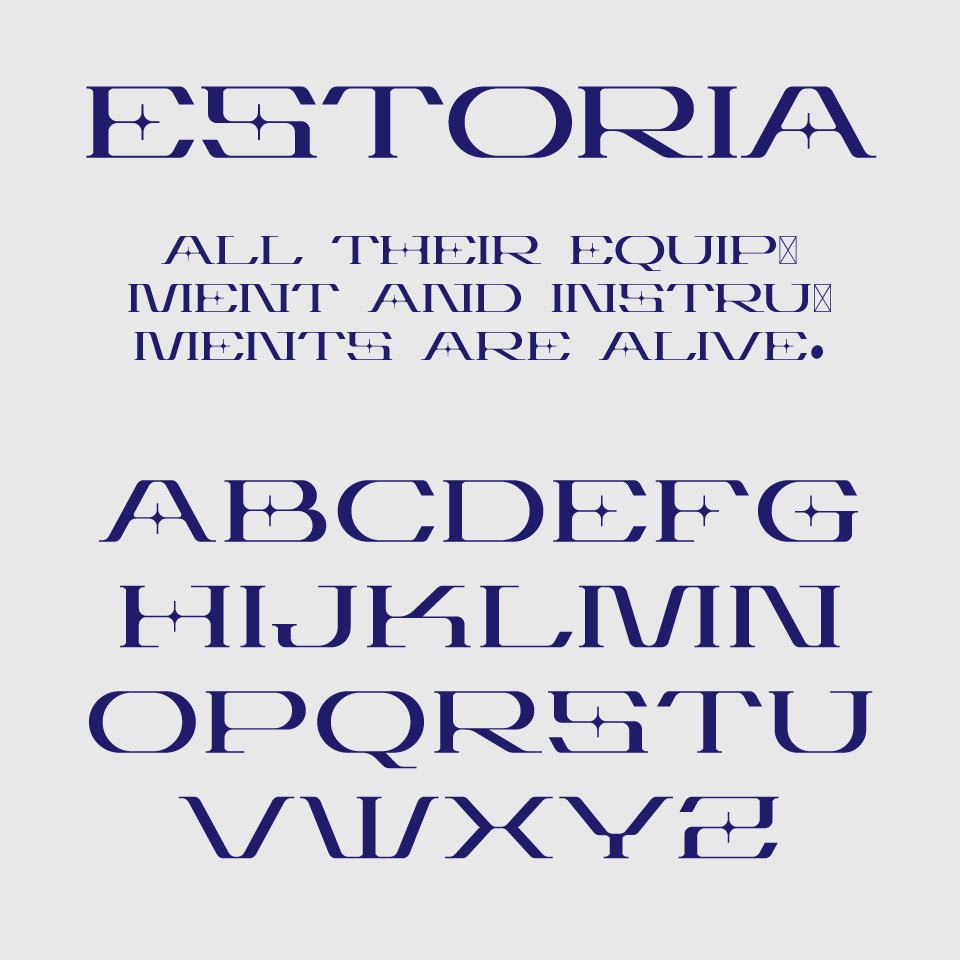
Estoriaフォントは、星のような装飾が特徴的な、美しくもミステリアスなディスプレイ書体です。SF映画や幻想的な世界観を思わせる繊細なデザインで、ひと文字ずつに物語があるような印象を与えてくれます。
クラシカルな骨格をベースにしつつ、未来的なムードも漂っており、非日常の雰囲気を演出したいときにぴったり。タイトルやロゴに使うだけで、世界観がぐっと引き立つフォントです。
収録文字は、大文字の収録となっています。
| 小文字 | × |